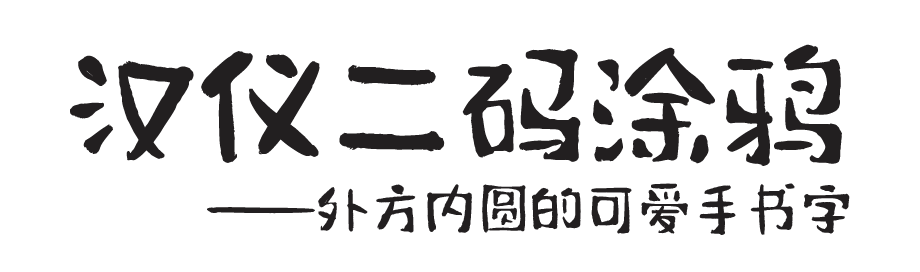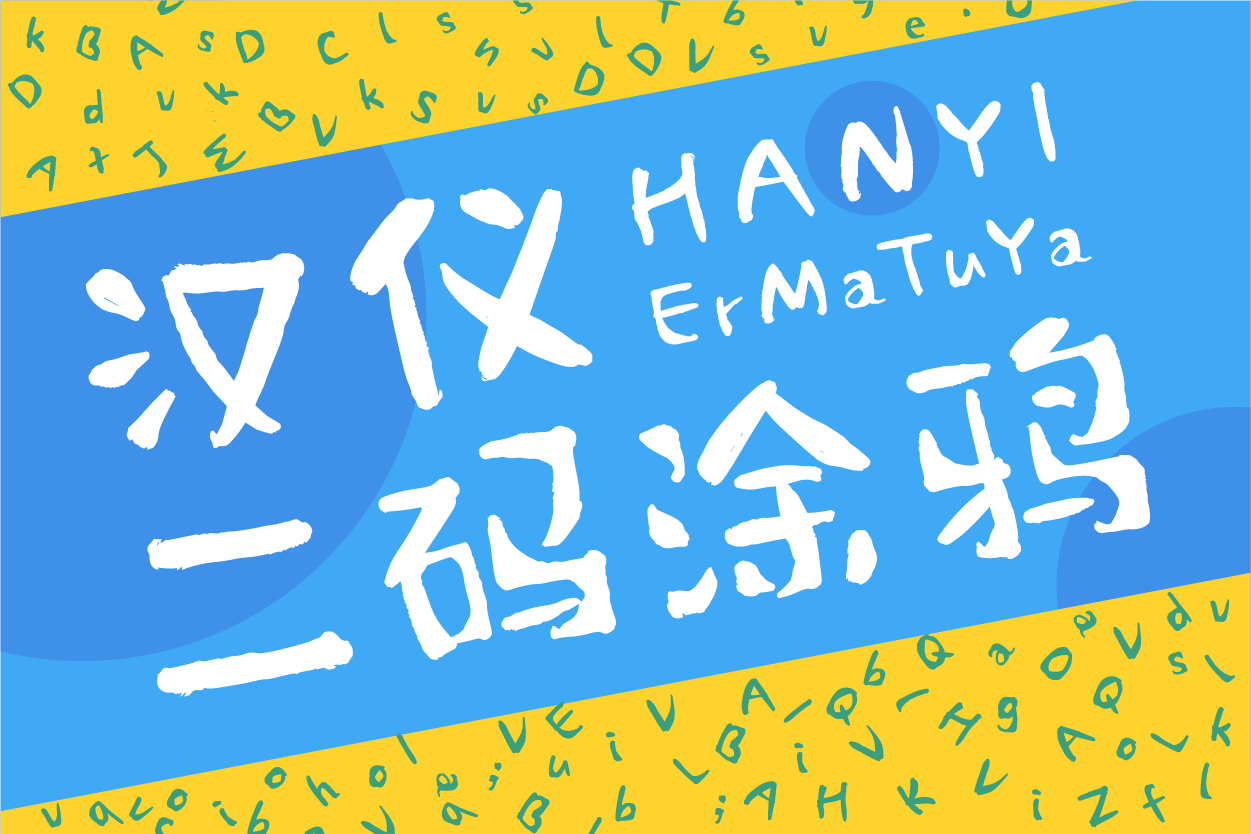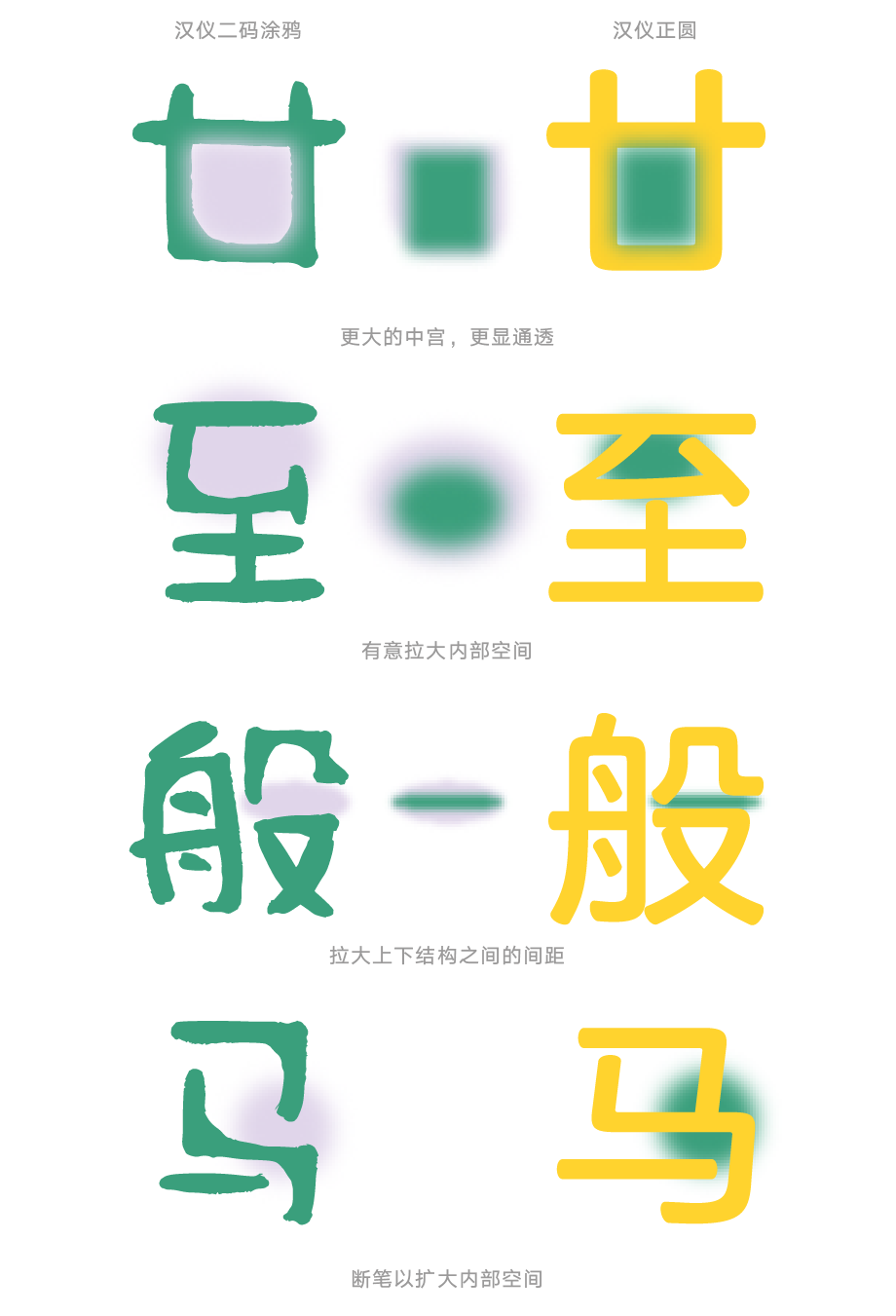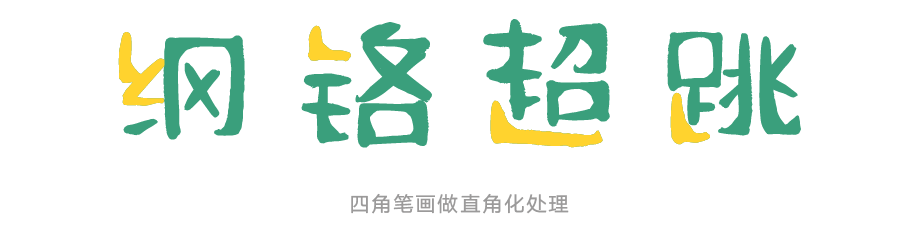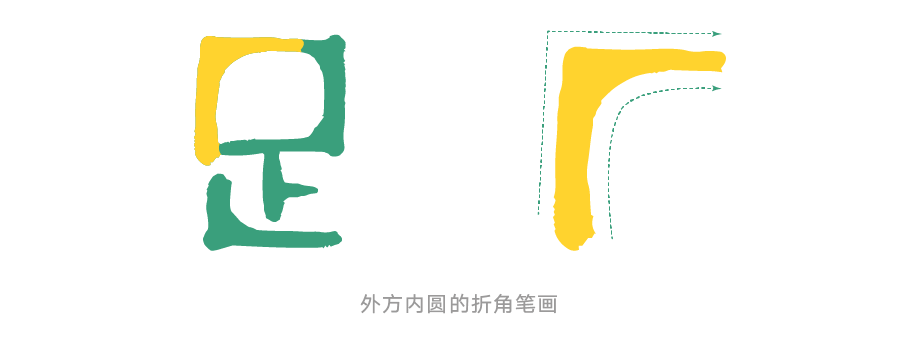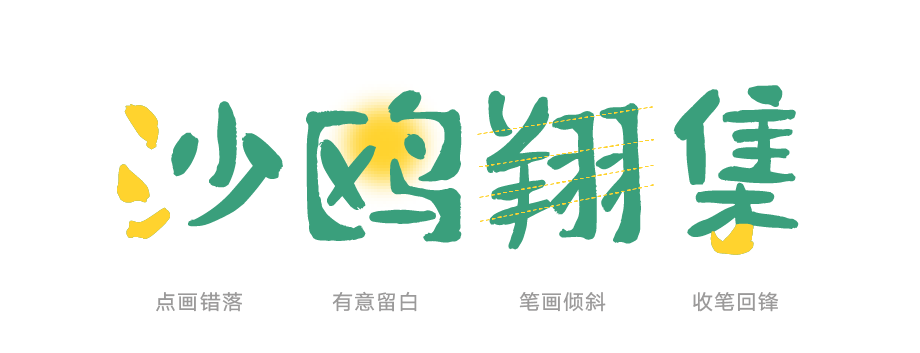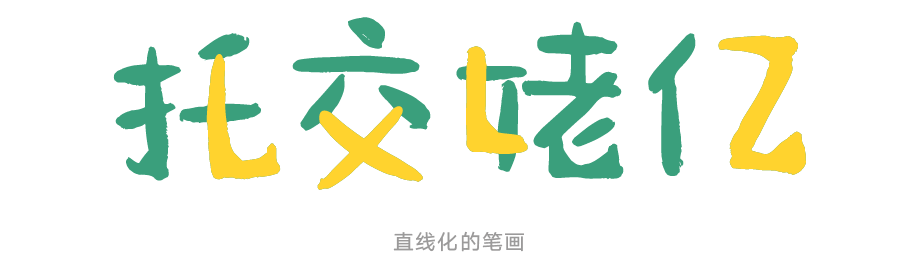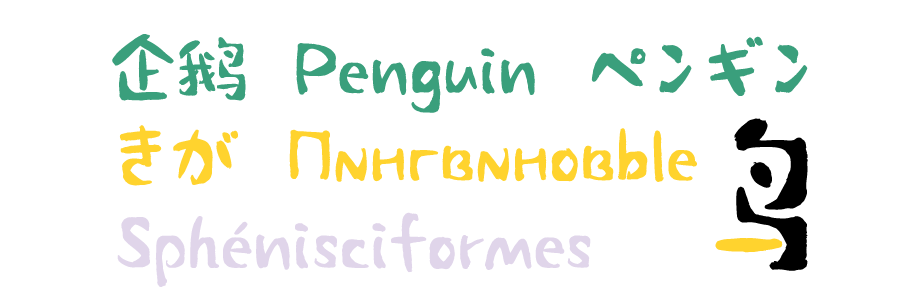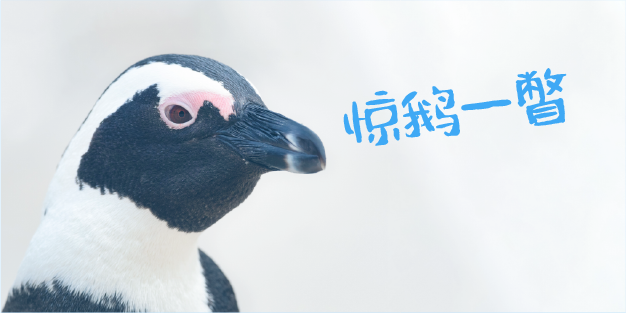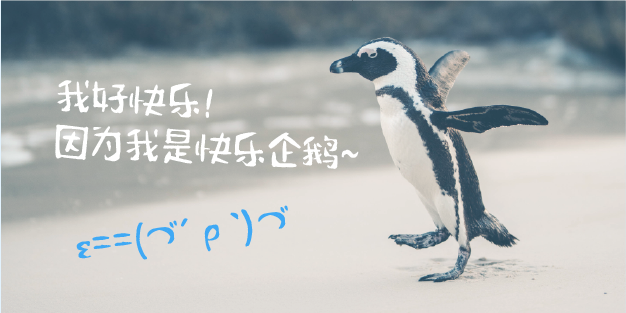
手书
汉仪二码涂鸦 | 字体介绍
汉仪二码涂鸦出自汉仪字库签约设计师泥二码,她擅长“手绘板书写”,是一位爽朗大方的东北姑娘。该款字体是汉仪字库与二码合作的第三款字体。
汉仪二码涂鸦是一款憨厚可爱的创意书写字体,这款字看起来摇摇晃晃,像是一群憨态可掬的企鹅,非常适合用于文创、动画等需要展现小清新或率真风格的场合。可用来排一些标题和短文案。
汉仪二码涂鸦 | 造型外方内圆
汉仪二码涂鸦有着较小的字面率,并且在字形内部刻意做了大量留白,使得字形在视觉效果上更加通透,给字形带来一定程度的陌生感。结构上中宫放松、中心偏低,使字形更显可爱率真。
设计师在设计这款字体时有意让笔画撑满整个空间,对诸多偏旁和笔画结构的造型进行了调整,使得字形看起来更“方”、更饱满。
在细节处理上,该字体折角处外部边缘接近直角,内部边缘做成了圆弧状,就像老相片四周的暗角一样,加深了折角处的灰度,也加深了外方内圆的暗示。
汉仪二码涂鸦 | 笔画慵懒随意
汉仪二码涂鸦在笔画造型上处理的更加慵懒随意:横笔竖笔有着不同的倾斜角度,增添摇晃感;部分交叉笔画错落摆放,给字形增添层次感。
设计师将部分带有弧度的笔画拉直或者转成折角,让字体看起来更“方”、更稚拙、更随意。
汉仪二码涂鸦 | 中西文匹配
汉仪二码涂鸦的外文部分也由作者泥二码绘制,除了常规的拉丁字母外,作者还绘制了部分扩展拉丁字母、西里尔字母和日语假名。外文继承了中文外方内圆的特征,风格一致,匹配和谐。
汉仪二码涂鸦 | 排版样张
汉仪二码涂鸦 | 中西文匹配